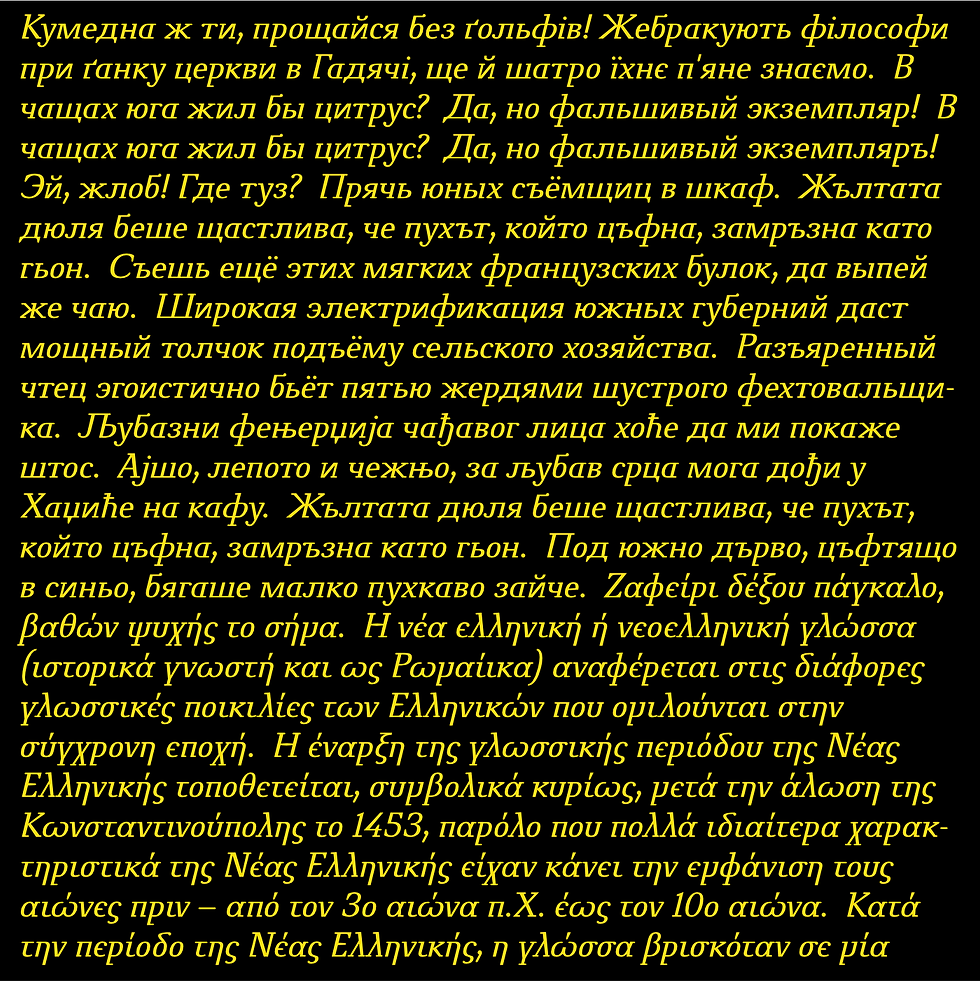
Eine nüchterne Antiqua mit runden Serifen und modernen Details
Soweit vertretbar wurde bei dieser Schrift aller traditionelle Ballast über Bord geworfen.
Ziel beim Gestalten der Novello war es, eine robuste Gebrauchs-Antiqua zu schaffen, die auch auf minderwertigen Papieren gut druckbar ist und auch unter widrigen Umständen gut lesbar bleibt.
In der Novello sorgt noch der Wechsel zwischen fetten Grundstrichen und feineren Haarstrichen für einen Rest Tradition.Die Buchstaben-Grundformen entsprechen der allgemein als richtig empfundenen traditionellen Gestalt. Die kurzen runden Serifen sind rechtwinklig an den Buchstabenkörper angefügt. Der Wechselzug folgt konstruierten Gesetzmäßigkeiten. Auffälligstes Merkmal der Novello ist der waagerechte Haarstrich sowie die Einläufe in den Grundstrich bei a, b, d, h n, m, p, q, r, u.
Die typische, aus dem Schreiben herrührende sanfte Bewegung des Anstrichs aus dem Grundstrich heraus ist vollkommen aufgelöst und gebrochen, so daß bei allen genannten Buchstaben eine horizontale Bewegung mit Betonung des rechten Winkels entsteht. Unnötige Rundungen werden so vermieden, und die Anmutung der Schrift erinnert fast an eine moderne Serifenlose.
Von den Buchstaben g, t und u gibt es alternative Formen.
Wie fast alle ingoFonts enthält auch die Novello ein Versal-ß und ein langes s.
Zur Novello gehören auch zahlreiche Ligaturen, die das Satzbild geschlossener erscheinen lassen.
Die Alternativ-Formen und die Ligaturen lassen sich mithilfe von OpenType-Funktionen an- und abschalten.